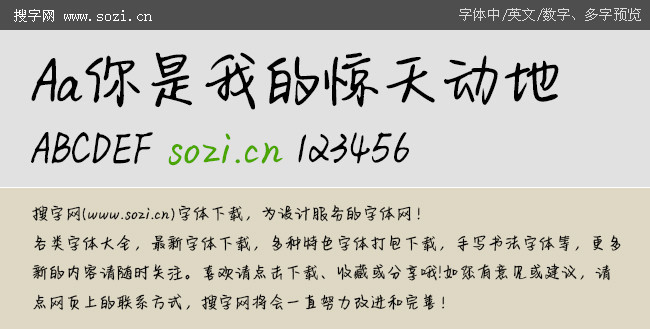
Aa你是我的驚天動(dòng)地字體
搜字網(wǎng)給大家提供一款A(yù)a你是我的驚天動(dòng)地字體中文字體下載,這是一款手寫風(fēng)格的書法字體,字體書寫自如,效果瀟灑大方,適合海報(bào)設(shè)計(jì)、包裝畫冊(cè)等宣傳廣告等應(yīng)用(此字體為個(gè)人非商用版,如需商用請(qǐng)聯(lián)系作者購買版權(quán))。